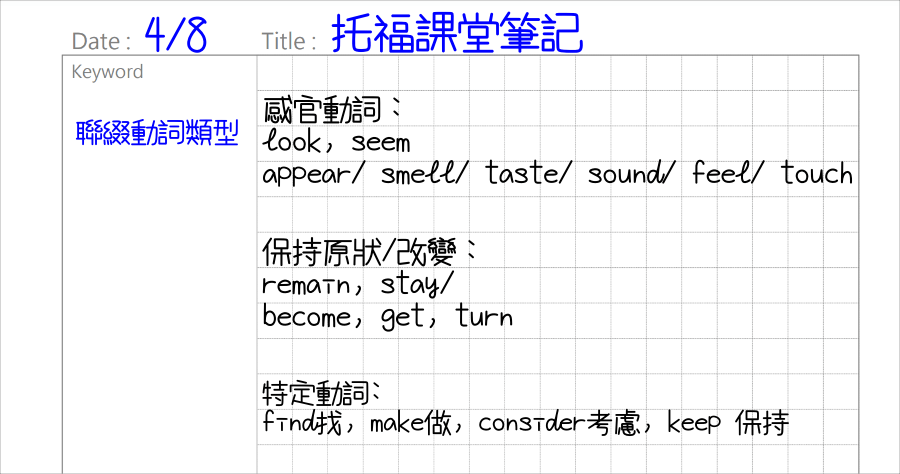
宅在家麥克筆 / 宅在家自動筆,2 款手寫免費可商用字體下載
你在找手寫字體嗎?最近小編發現網友自製 2 款手寫字體,分別是宅在家麥克筆、宅在家自動筆,由網友自主開發的兩款「手寫字體」,完全免費提供給大家下載,且不論個人、商業使用皆可,無使用限制,如果你正在找麥克筆字體、手寫字體,或是電腦還沒有同風格的字體,趕快將這兩款收下囉。另外還有一款我個人覺得很有手寫溫度的 851手書き雑フォント也是我自己常用的手寫字體,有需要的朋友自行前往收下囉。
宅在家麥克筆
上圖為「宅在家麥克筆」字體,不論英數、符號、注音、日文、中文通通支援,作者完全免費提供給大眾免費使用,個人、商業使用完全無限制。「宅在家麥克筆」也不斷的有在更新,以下為更新紀錄:
2020/01/26
修正部分文字寫法以及粗細未統一的錯誤
2020/02/09
優化木、禾以及米部文字寫法
2020/04/12更新
修正錯字「港」、「卧」「冗」,以及修正部分週期表元素用字未正常顯示的錯誤
2020/06/05更新
修正錯置「飞」
宅在家自動筆
上面則是「宅在家自動筆」字體,同樣可免費商業使用,涵蓋 Unicode 編碼 CJK Unified Ideographs 從「一 (U+4E00)」到「鿕(U+9FD5)」 共計20950 字,兩種字體的載點幫大家整理在下方啦,有需要手寫字體的朋友請自行下載囉!